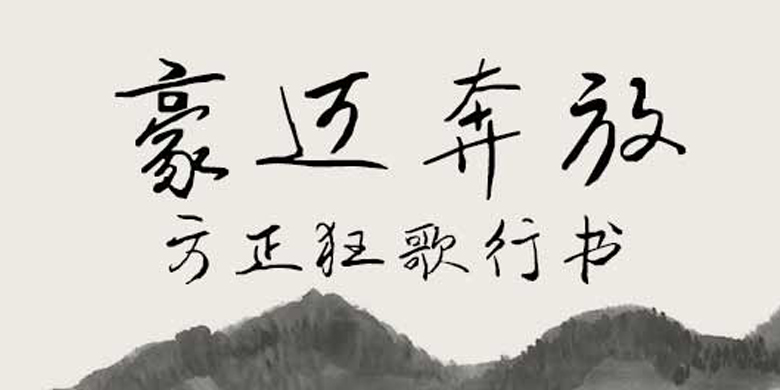
品牌:方正手迹设计师:金玉发行时间:2020字库编码:大陆简体(GB2312-80)分类:常规书写·硬笔字体属性:精品字
狂歌行书,字如其名,其字七分颠狂,三分漫不经心,任由性情挥散纸上。其形潇洒恣意,飘逸似仙,其态个性使然,气象万千。适用于文艺类的书刊、品牌广告和产品包装设计,以及社交网络的个性化用字。